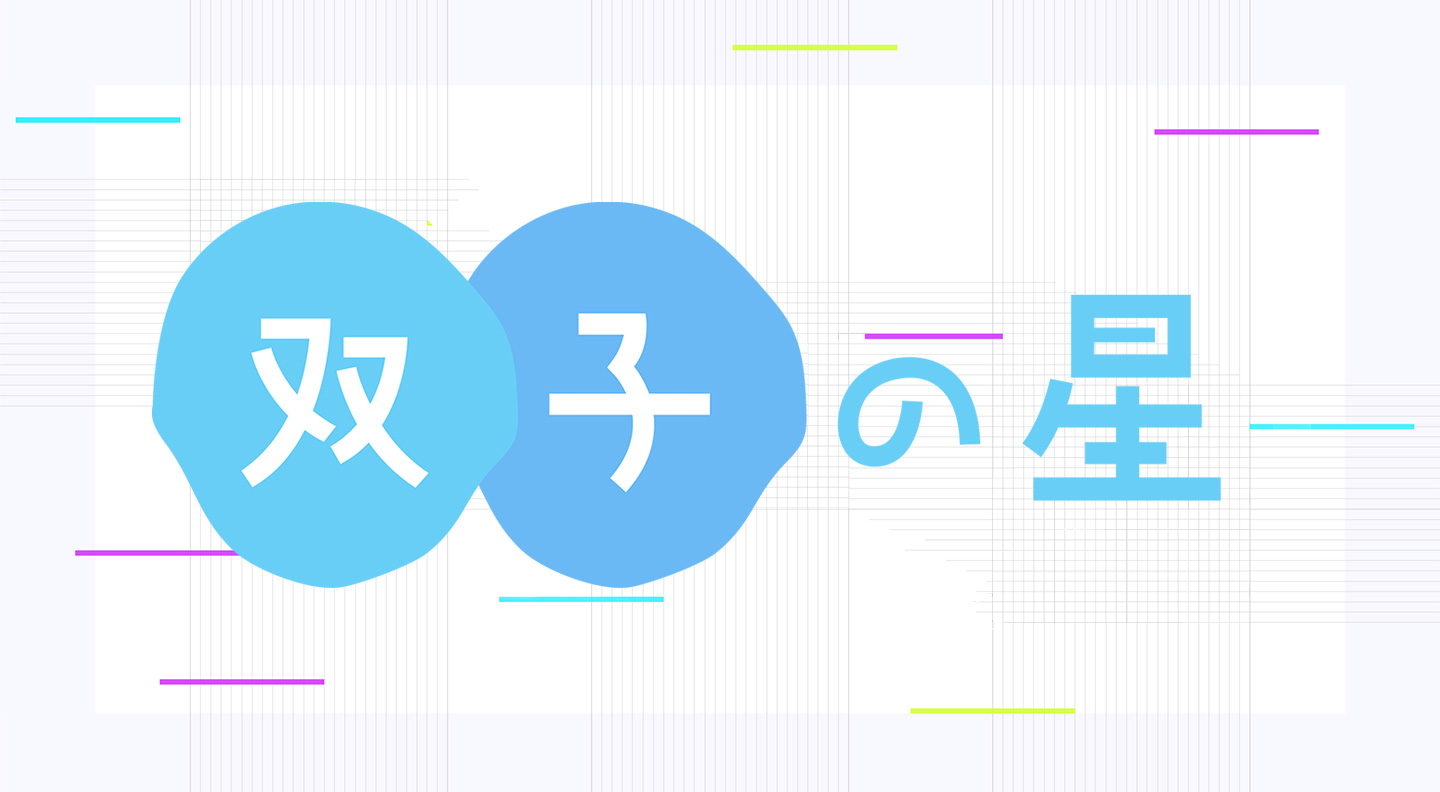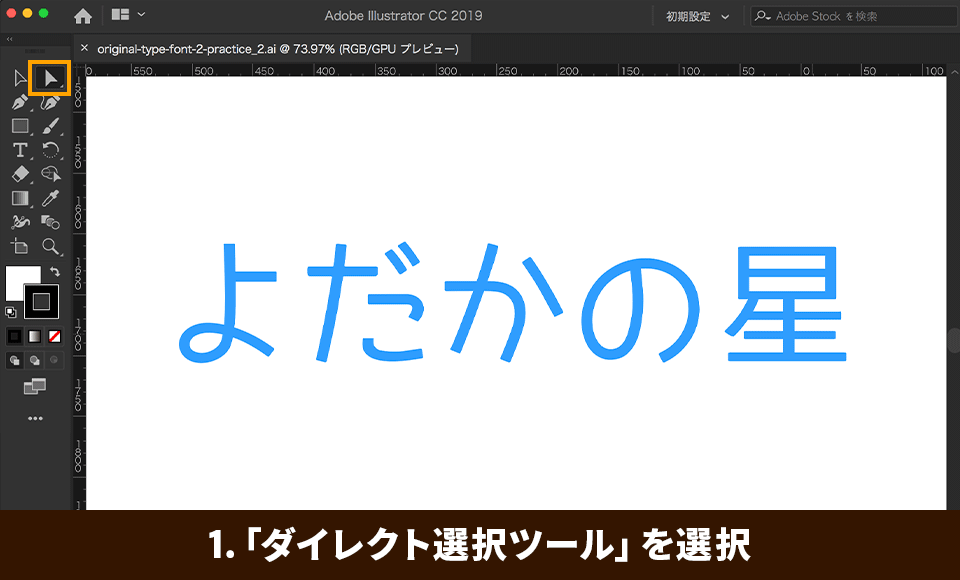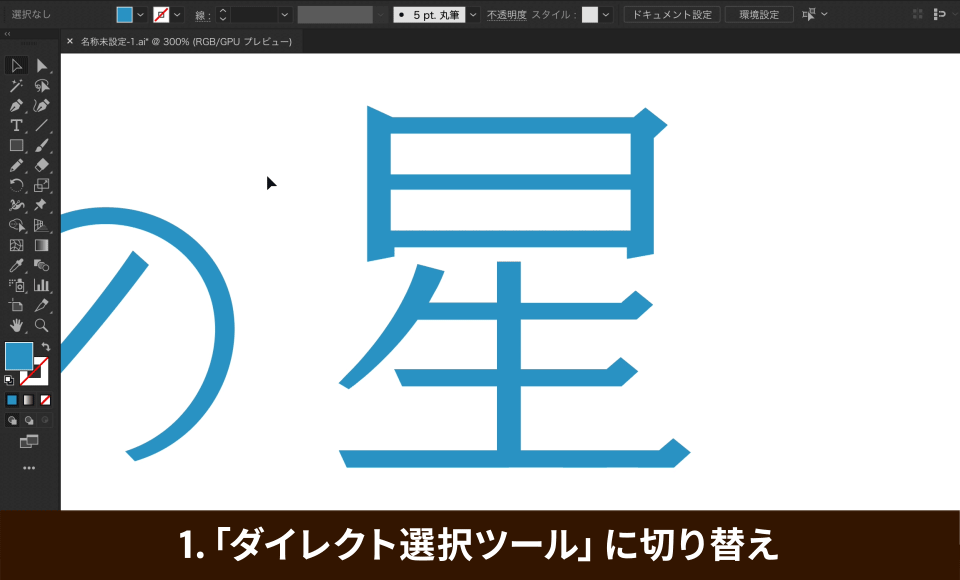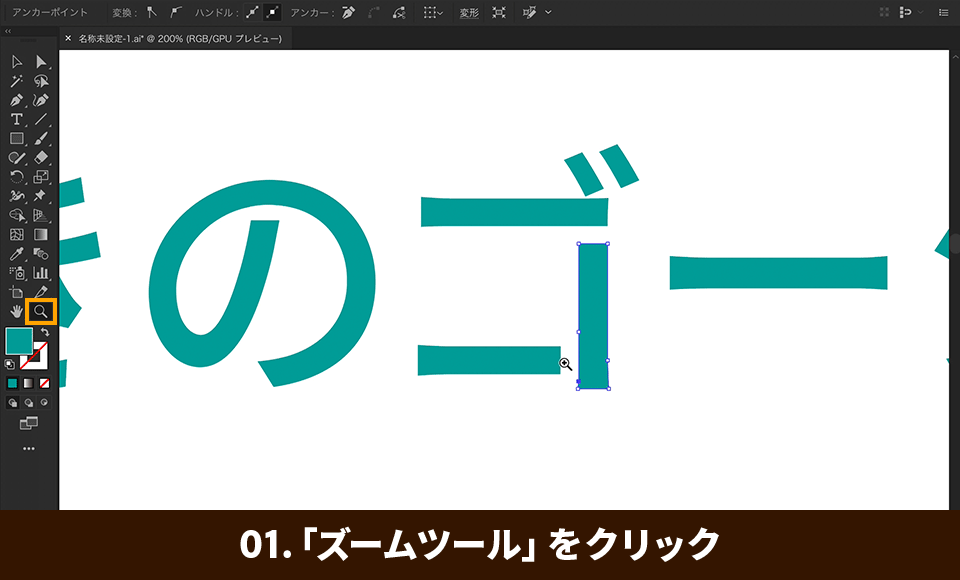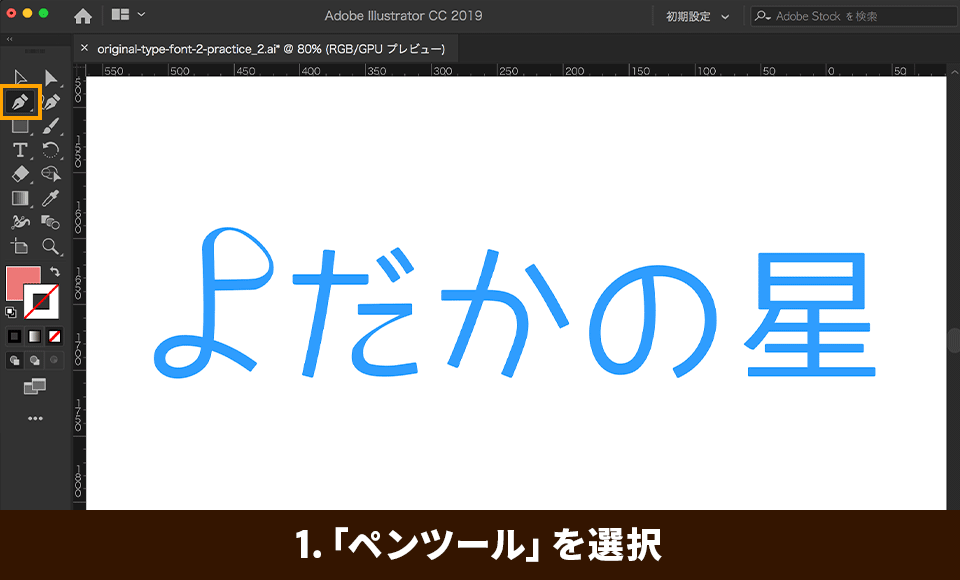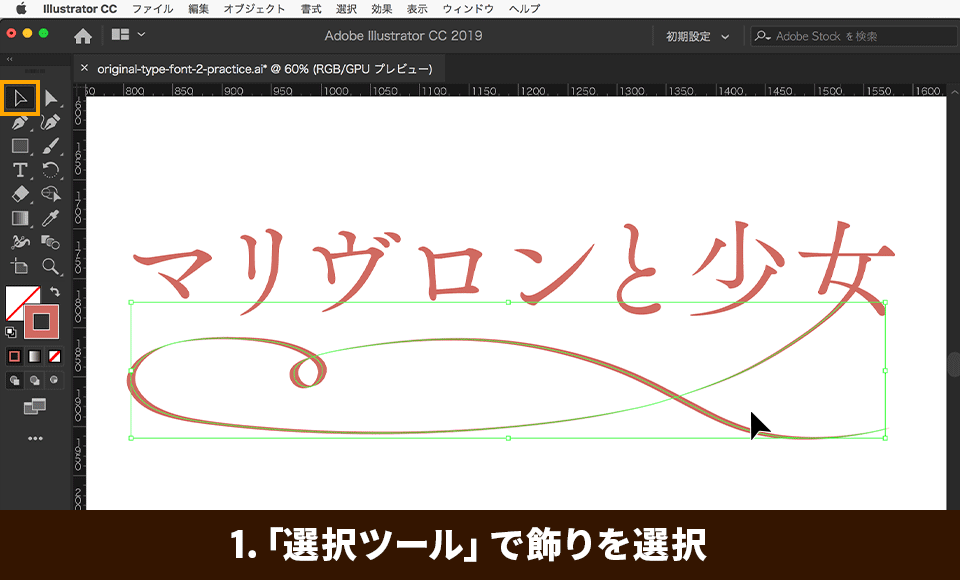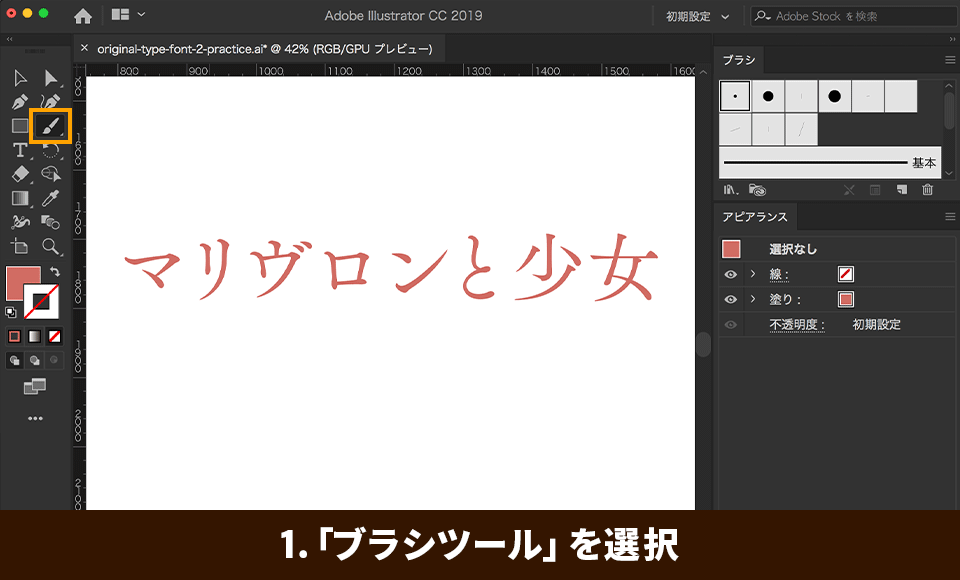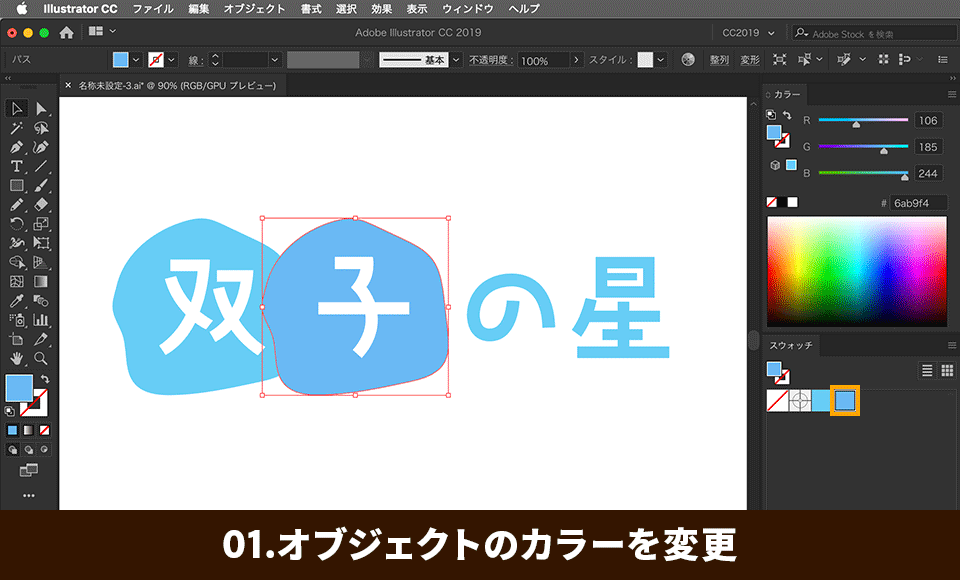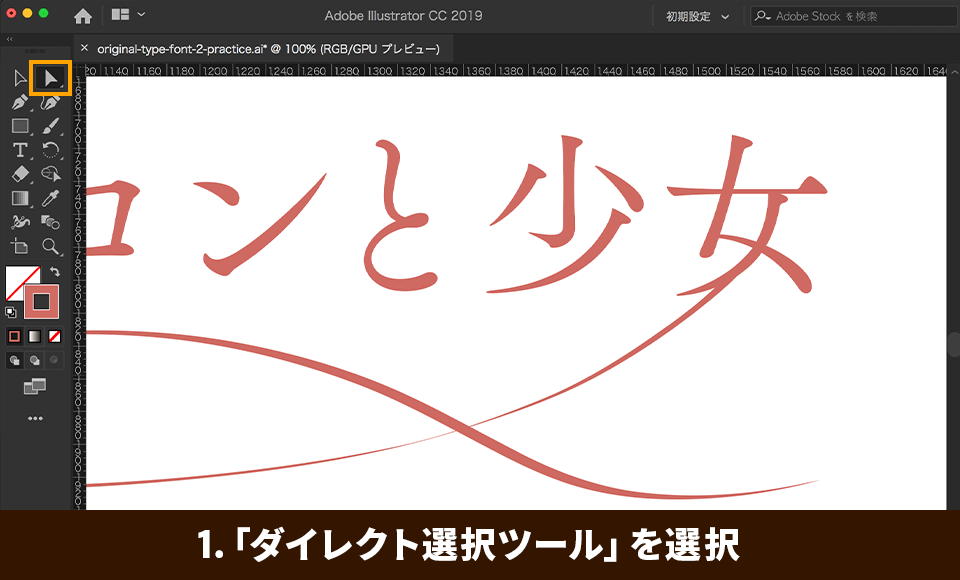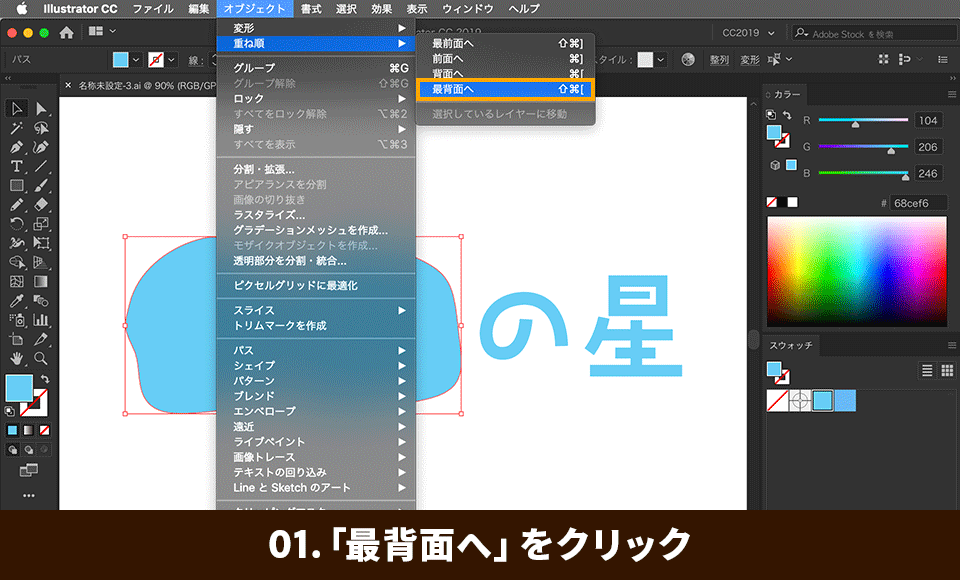
目を引く文字デザインの作成方法:中級編
日本語のタイトルやロゴをデザインするときにヒントとなりそうなアイデアと作り方を6個紹介します。既存のフォントをカスタマイズして、個性的なタイトル文字やロゴタイプを作成しましょう
本チュートリアルの概要
1. 文字の一部を分断
2. ワンポイントを入れる
3. 単純な線にする
4. 図形で囲む
5. 一部を伸ばす、つなげる
6. カリグラフィっぽい飾りを入れる
1. 文字の一部を分断する
1-1.
「文字ツール(T)」①を選択し、アートボード上をクリックして「セロ弾きのゴーシュ」というテキストを作成します②。
1-2.
入力した文字を選択した状態で、「文字パネル」(ウィンドウ → 書式 → 文字)を開きます。検索ボックス⓷の右にある「v」をクリックし、プルダウンのフォントメニュー④から使用したいフォントを選びます。
ヒント:
Illustratorでは、コンピューターにインストールされたフォント以外にも、Creative CloudのフォントサービスであるAdobe Fontsから様々な種類のフォントを検索して使用できます。「文字パネル」から表示したフォントメニューの「さらに検索」タブ①をクリックすると、Adobe Fontsで使用可能なフォントがすべて表示されます。使用したいフォントの右端にあるクラウドマーク②をクリックすると、フォントがアクティベートされ、Illustratorやその他のアプリで使用できるようになります。
1-3.
文字を個別のオブジェクトとして編集するため、パスデータに変換します。これをアウトライン化と言います。「選択ツール」で文字を選択し、「書式 」→ 「アウトラインを作成」をクリックします。
※文字をアウトライン化すると、テキスト情報が破棄されるため、フォントの変更や文字の打ち替えはできなくなります。
次にアウトライン化した文字を複合パスに変換します。複合パスとは、複数のパスを一つのパスとして扱うもので、パスが重なり合った部分は透明に抜けて表示されます。「オブジェクト」→「複合パス」→「作成」を選択し、複合パスを作成します。この時、オブジェクトの色情報がなくなってしまうため、色を再設定します。
これで文字を加工する準備が整いました。
1-4.
今回は文字にステンシル風の効果を加えます。ツールパネルから「長方形ツール(M)」を選択し、文字の繋ぎ目に長方形のパスを作成していきます。長方形の色を文字と違う色にすると、境目がわかりやすくなります。また、アートボードの色と同じ「白」にすると、完成イメージに近い状態で作業することができます。
1-5.
1-4で作成した長方形のパスを全て選択し、これらも複合パスへ変換します(オブジェクト → 複合パス → 作成)。次に、文字と長方形の複合パスを選択し、「パスファインダーパネル」(ウィンドウ → パスファインダー)の「前面のオブジェクトで型抜き」をクリックすると、文字が分断されます。
1-6.
「ズームツール」で分断した箇所を拡大すると、意図した通りに切り抜かれていない場合があります。その場合は、
「ダイレクト選択ツール(A)」や「ペンツール(P)」を使って分断した箇所のパスを整えましょう。
2. ワンポイントを入れる
2-1.
「文字ツール(T)」を選択し、アートボード上をクリックして「よだかの星」というテキストを作成します。次に、作成したテキストを選択し、「文字パネル」(ウィンドウ → 書式 → 文字)から使用するフォントを選びます。
2-2.
「選択ツール(V)」でテキストを選択し、「書式 」→ 「アウトラインを作成」を選択してテキストをアウトライン化します。フォントをアウトライン化する方法については「1-3」をご覧ください。
2-3.
今回は、「星」の文字にワンポイントを追加します。「ダイレクト選択ツール(A)」を使って、「星」の部首「日」の下のマドを選択し、Deleteキーを2回押して削除します。次に、上のマドの下辺を選択し、矢印キー「↓」を押して下に伸ばします。これでマドが1つになりました。
2-4.
次にワンポイントとなるオブジェクトを作成します。「長方形ツール(M)」 ① を選択し、マドの中をクリックすると ②、 ダイアログが表示されます。「縦横比を固定」をクリックして無効にし③、「幅」を指定します④。「OK」ボタンをクリックすると正方形が作成されます⑤。
2-5.
「選択ツール」を選択し、正方形の角にカーソルを当てると回転マークに変わるので、「Shiftキー」を押しながら45 度回転させます。
次に、「オブジェクト」→「変形」→「個別に変形」を選択します。ダイアログが表示されるので、「水平方向」を「20%」に設定し、「OK」ボタンをクリックします。細長いひし形ができました。
2-6.
ひし形を選択した状態で、「オブジェクト」→「変形」→「回転」を選択します。ダイアログが表示されるので「角度」を「45°」に設定し、「コピー」をクリックします。すると、回転前のひし形を残した状態で、45°回転したひし形が複製されます。
さらに、複製されたひし形が選択された状態で、「オブジェクト」→「変形」→「回転」を選択します。今度はダイアログで「角度」を「90°」に設定し、「コピー」をクリックします。
最後に、複製した2つのひし形を選択し、「オブジェクト」→「変形」→「拡大・縮小」を選択します。ダイアログが表示されるので「縦横比を固定」を「85%」に設定し、「OK」をクリックします。これで星マークが完成しました。
最後に、アンカーポイントやパスの編集をおこない、マドの部分をユニークに変形させてみましょう。
3. 単純な線にする
3-1.
最初にどんなイメージで文字を作るか、スケッチを描いてみましょう。下の図のように補助線があるノートを使用すると、文字の大きさが整った状態でデザインすることができます。
3-2.
スケッチが描き終わったら、スキャナーやスマホのカメラで取り込み、Illustratorへ配置します。「ファイル」→「配置」 ① を選択し、ダイアログで配置する画像を選択し ② 、「配置」 ③ をクリックします。
3-3.
配置したスケッチをトレースしていきます。この時、ノートの補助線の役割を果たすガイド線を利用すると、作業がやりやすくなります。「表示」→「定規」→「定規を表示」を選択すると、ワークスペースの上部と左側に定規が表示されます。
上部の定規をクリックし、そのまま下にドラッグして文字の頂点になる位置で指を離します。すると水平方向のガイド線が作成されます。同じ要領で、作成の目安になる位置にガイド線を引いていきましょう。左側の定規からは垂直方向のガイド線を引くことができます。
3-4.
「レイヤーパネル」(ウィンドウ → レイヤー)で、配置したスケッチのレイヤーを選択し、「透明パネル」(ウィンドウ→ 透明)の「不透明度」を「25%」 ① に設定します。スケッチが半透明になったら、レイヤーの目のマークの右側をクリックし、ロックをかけます ② 。
次に、レイヤーパネルの下部にある「新規レイヤー」ボタン ③ をクリックして、新しいレイヤーを作成し、ここにペンで文字を描いていきます。
3-5
ツールパネルで「ペンツール(P)」 ① を選択し、塗りと線を入れ替えて「線」が選択された状態にします ② 。「カラーパネル」(ウィンドウ → カラー) ③ で好みの色を指定します(ここでは、R:154、G:157、B:254)。
次に、「線パネル」(ウィンドウ → 線) ④ で線幅を「5pt」に指定します。
3-6.
下絵のスケッチとガイド線を参考に、ペンツールで線(パス)を描いていきます。アートボード上をクリックし、クリックしたポイントとポイントの間が直線で結ばれます。パスの長さは、長・中・短の3パターンのみにし、隣り合う文字のX軸を意識して組んでいくとバラツキがなく綺麗に仕上がります。
ヒント:レイヤーパネルでスケッチのレイヤーの左端にある目のマークをクリックすると、レイヤーが非表示になり、実際の仕上がり具合が確認できます。また、「表示」→「ガイド」→「ガイドを隠す」を選択すると、ガイド線が非表示になります。
3-7.
「詩」の「口」と「、」の部分は円にしたいので「楕円形ツール(L)」 ① を使って作成します。「Shift」キーを押しながらドラッグすると正円が描けます ② 。
3-8.
描き終えたら、描いた全てのパスを選択し、「メニュー」→「オブジェクト」→「パス」→「パスのアウトライン」を 選択してパスをアウトライン化します。これで完成です。
4. 図形で囲む
4-1
「文字ツール(T)」を選択し、アートボード上をクリックして「双子の星」というテキストを作成します。次に、作成したテキストを選択し、「文字パネル」(ウィンドウ → 書式 → 文字)から使用するフォントを選びます。
4-2.
「カラーパネル」(ウィンドウ → カラー)で文字の色を指定します。「塗り」が選択された状態で、スライダーをドラッグまたは数値を入力します。
4-3.
テキストを選択した状態で、「書式 」→ 「アウトラインを作成」をクリックし、テキストをアウトライン化します。フォントをアウトライン化する方法については「1-3」をご覧ください。
次に、文字を1つずつ個別に扱えるよう、「オブジェクト」→「グループ解除」を選択して、テキストのグループ化を解除します。「選択ツール」で「双」と「子」をそれぞれ移動させます。
4-4.
「鉛筆ツール(N)」を選択して、「双」の字の周りを囲むように円を描きます。透明のパスが作成されるので、ツールパネルの「カラー」をクリックすると、文字色と同じ色が適用されます。
※ツールパネルの「カラー」には前回使用したカラーが保存されています。別のカラーを指定する場合は、カラーパネルで任意の色を指定します。
次に「選択ツール」に切り替えて、作成したパスを選択し、「Alt(Option)+Shift」キーを押しながら右方向にドラッグします。パスが複製されるので、「子」が中央に収まるあたりで指を離します。
4-5.
作成したパスが文字よりも上の位置にあるため、文字が表示されません。2つのパスを選択し、「オブジェクト」→
「重ね順」→「最背面へ」を選択すると、パスが文字よりも下の位置へ移動します。
文字とパスが同じ色のため、「双」と「子」を選択し、カラーパネルで文字の色(塗り)を白に変更します。
4-6.
「子」を囲っているパスを選択して、色を変更します。濃い色に変更したこともあるのですが、「子」のパスが「双」の上に来ているのは文字の読み順として違和感があるため、メニューから「オブジェクト→重ね順→最背面へ」を選択し、背面へ移動させます。
4-7.
最後に全体のバランスを調整します。「の」だけ小さくしてメリハリをつけるなど、納得のいく仕上がりになるまで調整してみましょう。
6-6.
文字と飾りを合体させて1つのオブジェクトに変換します。文字と飾りを全て選択した状態で、「パスファインダーパネル」の「合体」をクリックし、パスを結合します。
6-7.
最後は、「ダイレクト選択ツール(A)」で気になる箇所を調整して、完成です。
いかがでしたか、普通の文字にひと手間加えれば、個性あふれるオリジナル文字へと変身させることができます。今回はパスの編集など、少し難しい操作もありましたが、慣れてくれば思い通りの描画ができるようになります。ここで学んだテクニックを活用し、より魅力的なタイトル文字を作成してみてください。